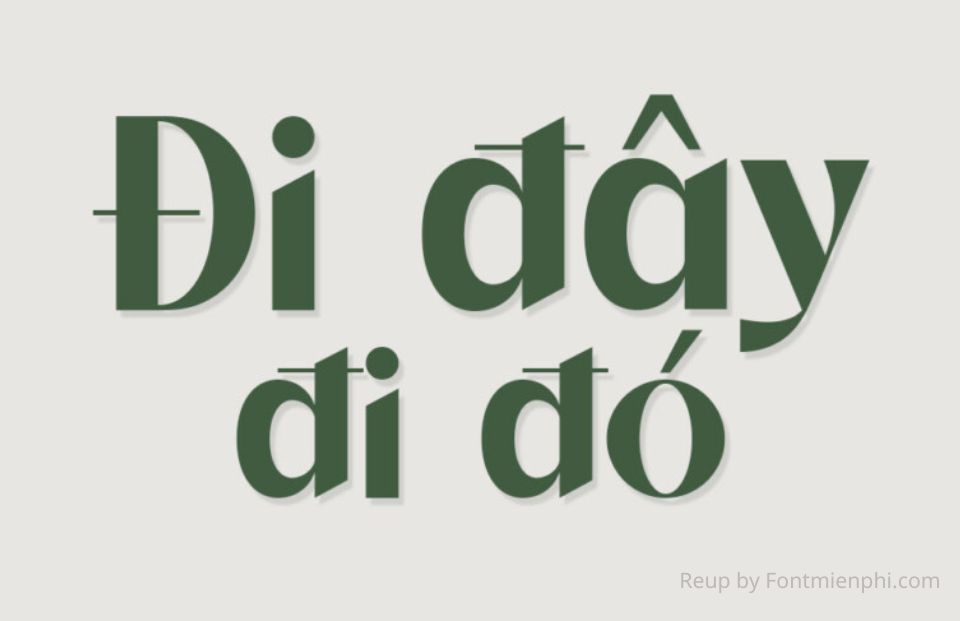
Font Việt Hóa 1FTV VIP Khaviax
Tải Font Việt Hóa 1FTV VIP Khaviax – Lựa Chọn Hoàn Hảo Cho Thiết Kế Hiện Đại
Trong thế giới thiết kế đồ họa và phát triển giao diện web, việc lựa chọn một phông chữ phù hợp không chỉ giúp truyền tải thông điệp mà còn định hình phong cách thương hiệu. Font Việt hóa 1FTV VIP Khaviax đang trở thành một trong những cái tên được giới designer đặc biệt quan tâm. Bài viết này sẽ giúp bạn hiểu rõ hơn về những ưu điểm vượt trội của bộ font này và cách ứng dụng nó hiệu quả vào các dự án số.
Tổng Quan Về Font 1FTV VIP Khaviax
1FTV VIP Khaviax là một bộ phông chữ cao cấp được thiết kế với những đường nét tinh tế, mang đậm tính nghệ thuật nhưng vẫn giữ được sự hiện đại. Điểm nhấn lớn nhất của phiên bản này là đã được Việt hóa hoàn chỉnh, hỗ trợ trọn vẹn bộ gõ tiếng Việt với các dấu câu được căn chỉnh (kerning) vô cùng tỉ mỉ.
Điều này giúp giải quyết triệt để tình trạng lỗi font hay lệch dấu, đặc biệt quan trọng khi bạn cần xử lý những đoạn text có kích thước lớn trên banner, landing page hay các dự án lập trình giao diện.
Đặc Điểm Nổi Bật Của 1FTV VIP Khaviax
Bộ font này mang lại nhiều giá trị thực tiễn cho các dự án thiết kế sáng tạo:
• Đường nét sắc sảo, độc đáo: Khaviax sở hữu cấu trúc chữ cân đối, tạo cảm giác sang trọng và chuyên nghiệp. Sự tương phản trong nét chữ giúp nó dễ dàng thu hút sự chú ý của người xem.
• Tối ưu dấu tiếng Việt (Optimized Typography): Các dấu câu được tinh chỉnh cẩn thận để hài hòa với từng con chữ, đảm bảo tính thẩm mỹ đồng bộ cho toàn bộ đoạn văn bản.
• Tính đa dụng cao: Phù hợp với nhiều phong cách khác nhau, từ thanh lịch, cổ điển đến hiện đại, phá cách.
• Khả năng hiển thị sắc nét: Render mượt mà trên các thiết bị kỹ thuật số, rất lý tưởng để ứng dụng vào thiết kế UI/UX hoặc tích hợp vào các theme WordPress chuyên nghiệp.
Ứng Dụng Thực Tế Trong Thiết Kế Và Web
Với đặc thù là một bộ font chất lượng cao, 1FTV VIP Khaviax có thể tỏa sáng trong rất nhiều hạng mục:
• Thiết kế nhận diện thương hiệu: Sử dụng làm typography chủ đạo cho Logo, Business Card, hay Profile doanh nghiệp.
• Ấn phẩm truyền thông (Social Media & Ads): Tạo các tiêu đề (Heading) bắt mắt trên banner quảng cáo Facebook, Google Ads, giúp làm nổi bật thông điệp cốt lõi.
• Thiết kế Website: Việc tích hợp một font chữ hiển thị đẹp, rõ nét trên các nền tảng web sẽ nâng tầm trải nghiệm người dùng, giúp tổng thể giao diện trở nên cao cấp hơn, đặc biệt khi kết hợp với các trình dựng trang (page builders).
• Nhiếp ảnh và Nghệ thuật: Rất thích hợp để chèn quote, typo nghệ thuật lên các bộ ảnh hoặc video.
1FTV VIP Khaviax không chỉ là một bộ phông chữ, mà là một công cụ đắc lực giúp các bản thiết kế đồ họa và giao diện kỹ thuật số trở nên sắc nét và chuyên nghiệp hơn. Sự kết hợp giữa đường nét thiết kế đẳng cấp và khả năng hỗ trợ tiếng Việt hoàn hảo chắc chắn sẽ đáp ứng tốt yêu cầu của những dự án thiết kế sáng tạo.